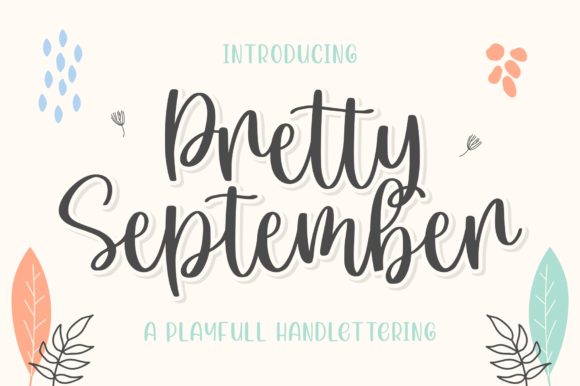
Pretty September
Ulasan Lengkap: Font Pretty September – Sentuhan Keren dan Ceria untuk Desainmu
Jika kamu sedang mencari font yang unik, ceria, dan mudah dipakai di berbagai proyek, Pretty September adalah jawaban yang sempurna. Font bergaya tulisan tangan ini menawarkan nuansa quirky yang membuat setiap teks terasa hidup dan penuh karakter. Berikut ulasan lengkap mengenai keunggulan, kegunaan, dan cara memaksimalkan Pretty September di desainmu.
1. Apa Itu Pretty September?
- Font tulisan tangan yang handwritten dengan gaya playful.
- Dirancang untuk menambah keceriaan pada teks.
- Ketersediaan berbagai gaya huruf: normal, bold, italics, dan sedikit variasi bentuk.
2. Kenapa Pretty September Cocok untuk Kamu?
- **Keterbacaan Tinggi** – Meskipun playful, hurufnya tetap jelas dan mudah dibaca.
- **Versatilitas** – Cocok untuk stationery, desain poster, banner, kartu ucapan, dan bahkan branding produk.
- **Mudah Disesuaikan** – Dapat dipadukan dengan warna-warna pastel, neon, atau kombinasi warna kontras.
- **Digital Friendly** – Ideal untuk social media posts, stories, dan ads karena tampil menarik di layar.
3. Cara Menggunakan Pretty September dalam Desain
- Selamatkan Keren**: Tambahkan heading atau subheading dengan Pretty September untuk memukau audiens.
- Tambahkan Efek Layer**: Gunakan drop shadow atau outline agar teks lebih menonjol.
- Warna Storytelling**: Cocok dipadukan warna pastel untuk tema musim semi atau warna bold untuk tema festival.
- Eksperimen dengan Komposisi**: Gabungkan dengan ilustrasi sederhana atau elemen geometris untuk hasil maksimal.
5. Kesimpulan
Pretty September bukan sekadar huruf—ia adalah sentuhan pribadi yang menambah joyful vibe dalam setiap karya. Baik untuk sesama desainer, pemilik usaha, atau siapa saja yang ingin mengekspresikan keunikan lewat teks, font ini memberikan fleksibilitas dan keanggunan sekaligus kesan hangat. Cobalah tambahkan Pretty September pada proyekmu sekarang, dan saksikan bagaimana desainmu menjadi lebih hidup dan memorable.